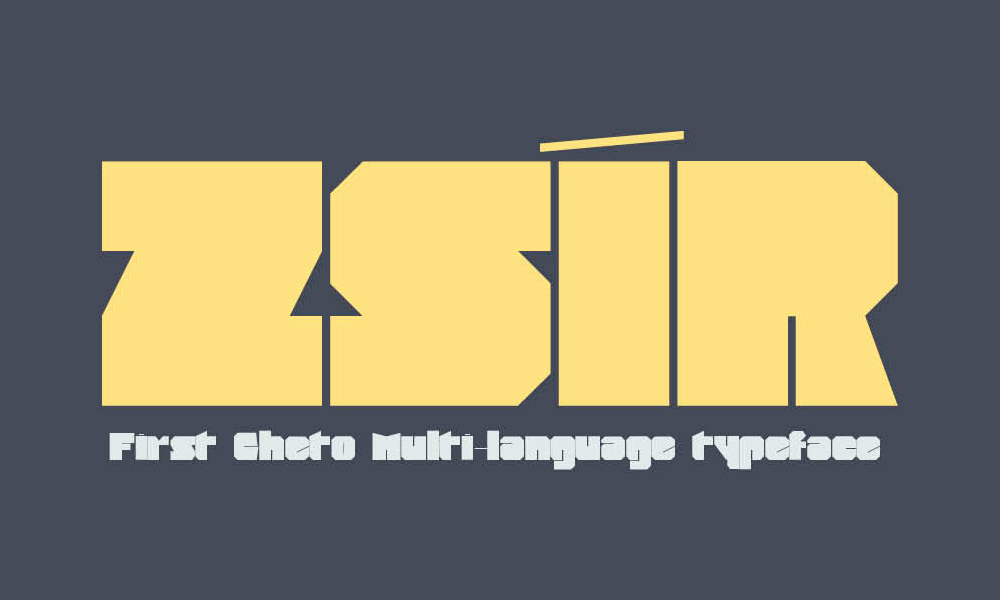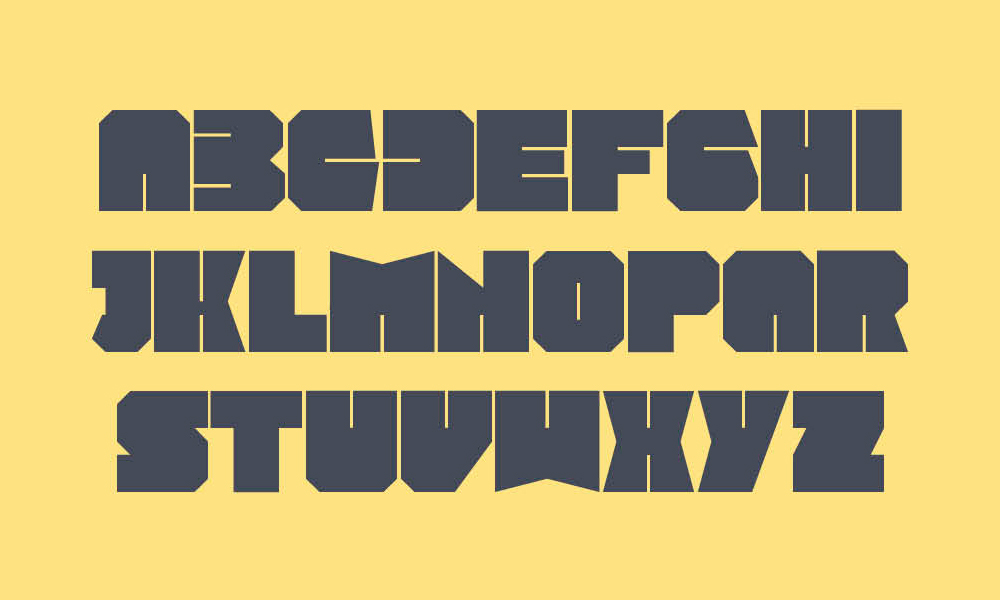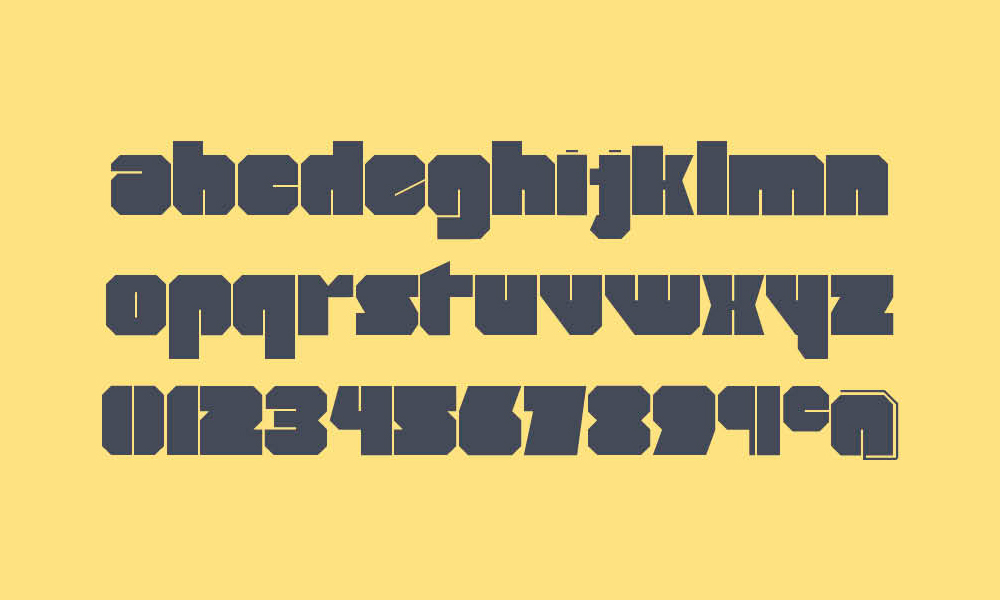
فونت پرمیوم و انگلیسی Zsir Font یک فونت نمایشی چندزبانه جذاب که برای ایجاد یک جلوه جسورانه طراحی شده است. Zsir با حروف ضخیم، علائم تفکیکی خاص و مجموعهای از حروف و علائم تفکیکی اضافی، یک تجربه تایپوگرافی منحصر به فرد را برای طراحانی که به دنبال یک فونت چشمگیر و همه کاره هستند، ارائه میدهد. Zsir با دقت و توجه به جزئیات ساخته شده است و ظرافت را با کمی بازیگوشی ترکیب میکند. حروف سنگین آن اعتماد به نفس را القا میکنند و تأثیر بصری قویای دارند و آن را برای تیترها، پوسترها، برندسازی و سایر برنامههای نمایشی ایدهآل میکنند. چه برای چاپ طراحی کنید و چه برای رسانههای دیجیتال، سبک متمایز Zsir مخاطبان شما را مجذوب خود خواهد کرد.
مزایای استفاده از فونت لاتین Zsir چیست؟